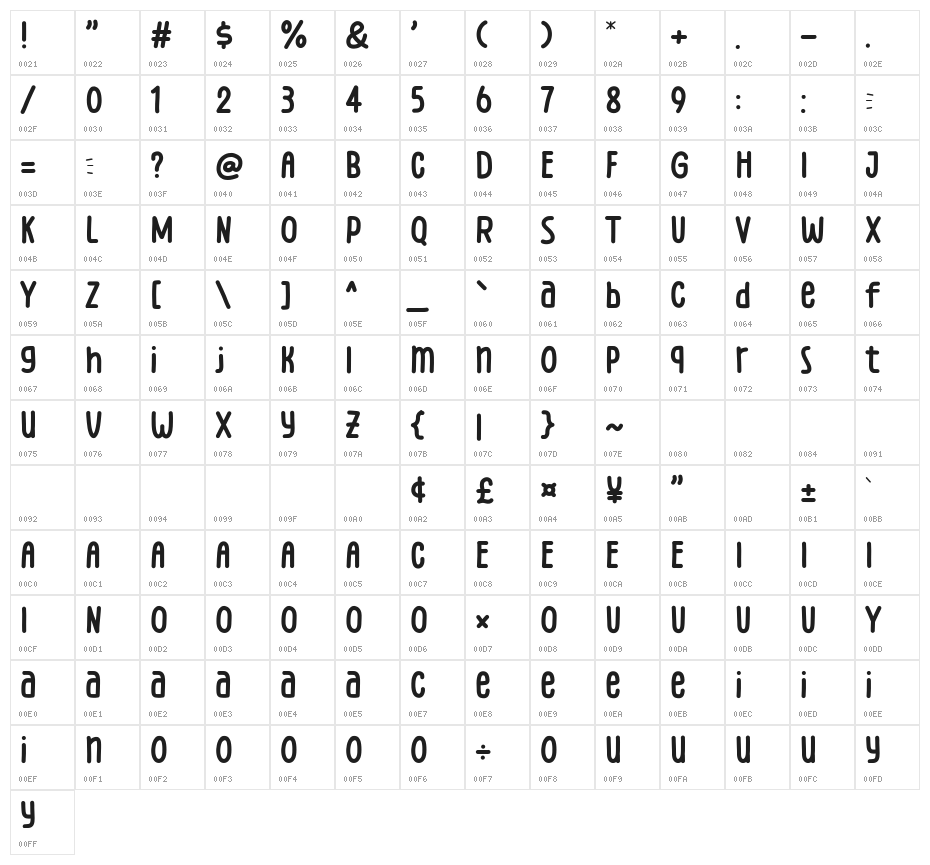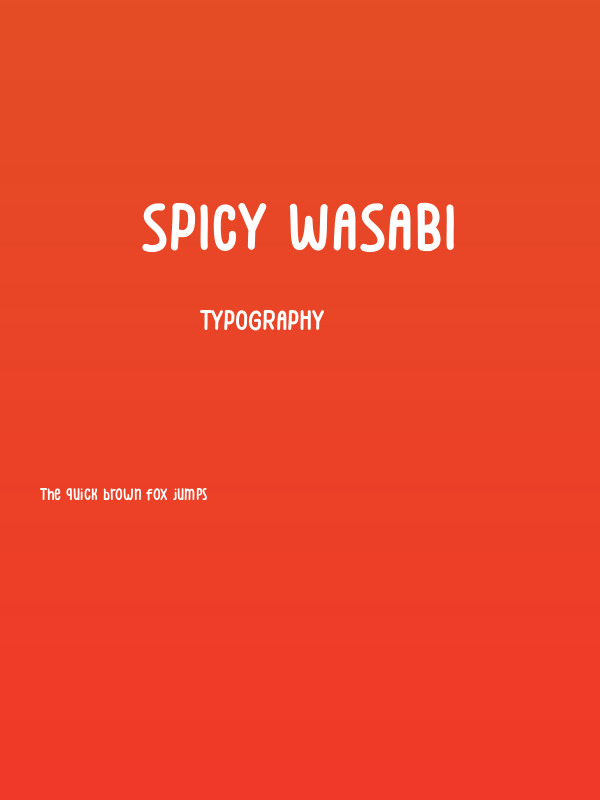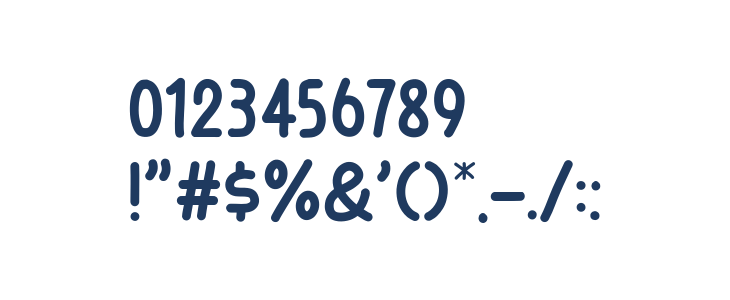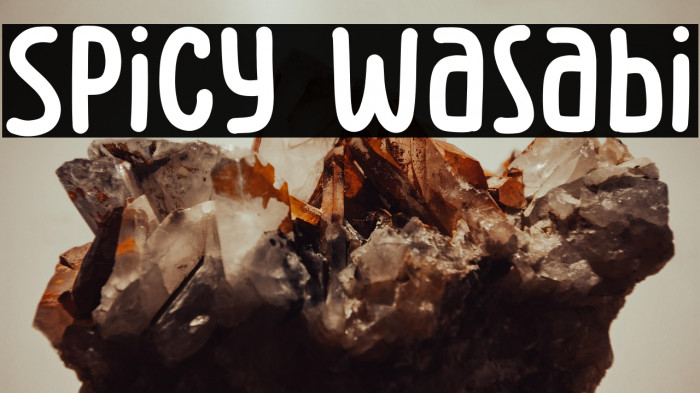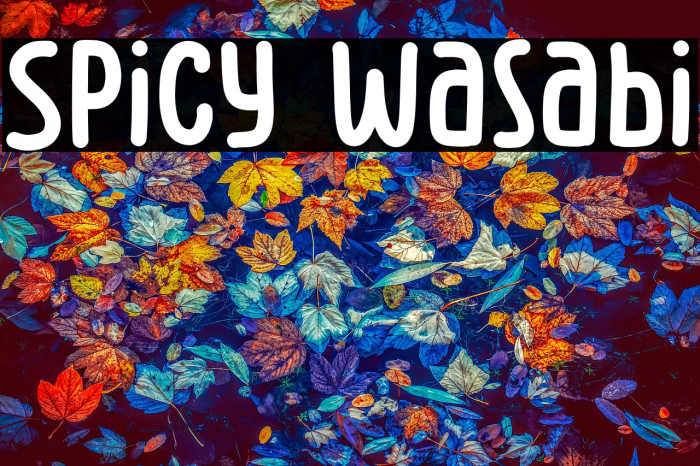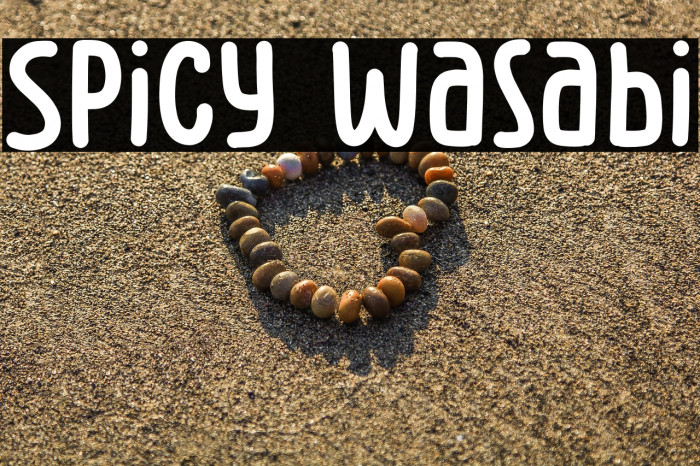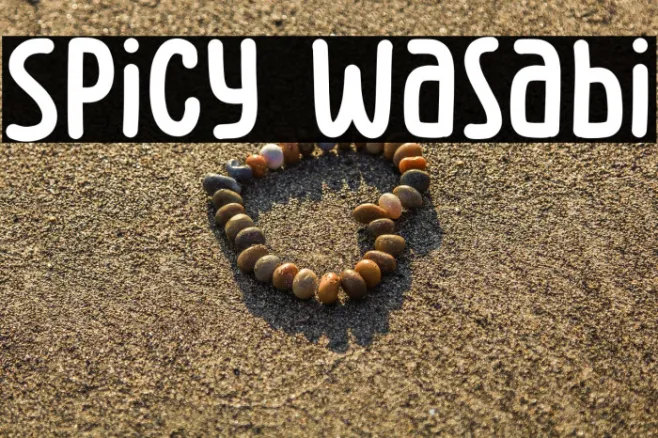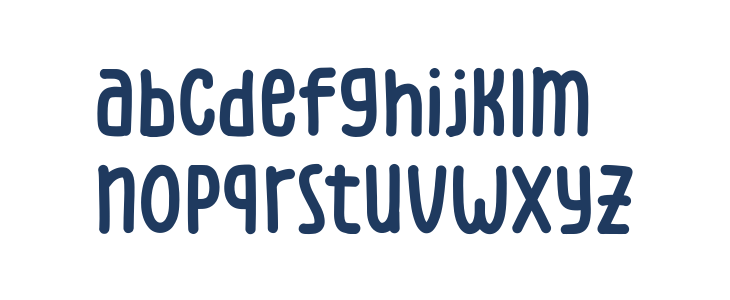
Spicy Wasabi Font
| Gesamtstil | Playful |
| Vorgeschlagene Projekte | Ideal for children's books, playful branding, posters, and social media graphics. |